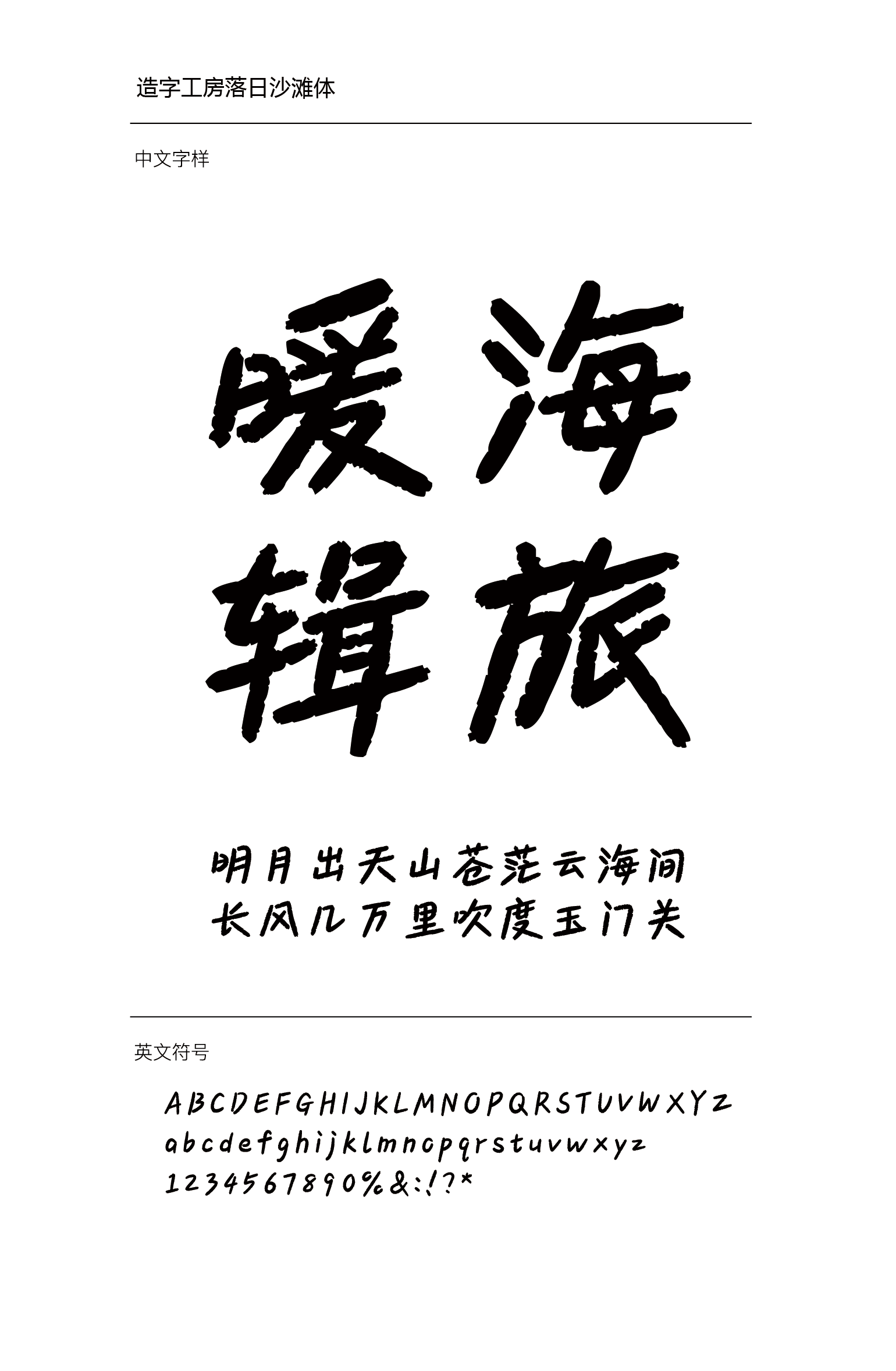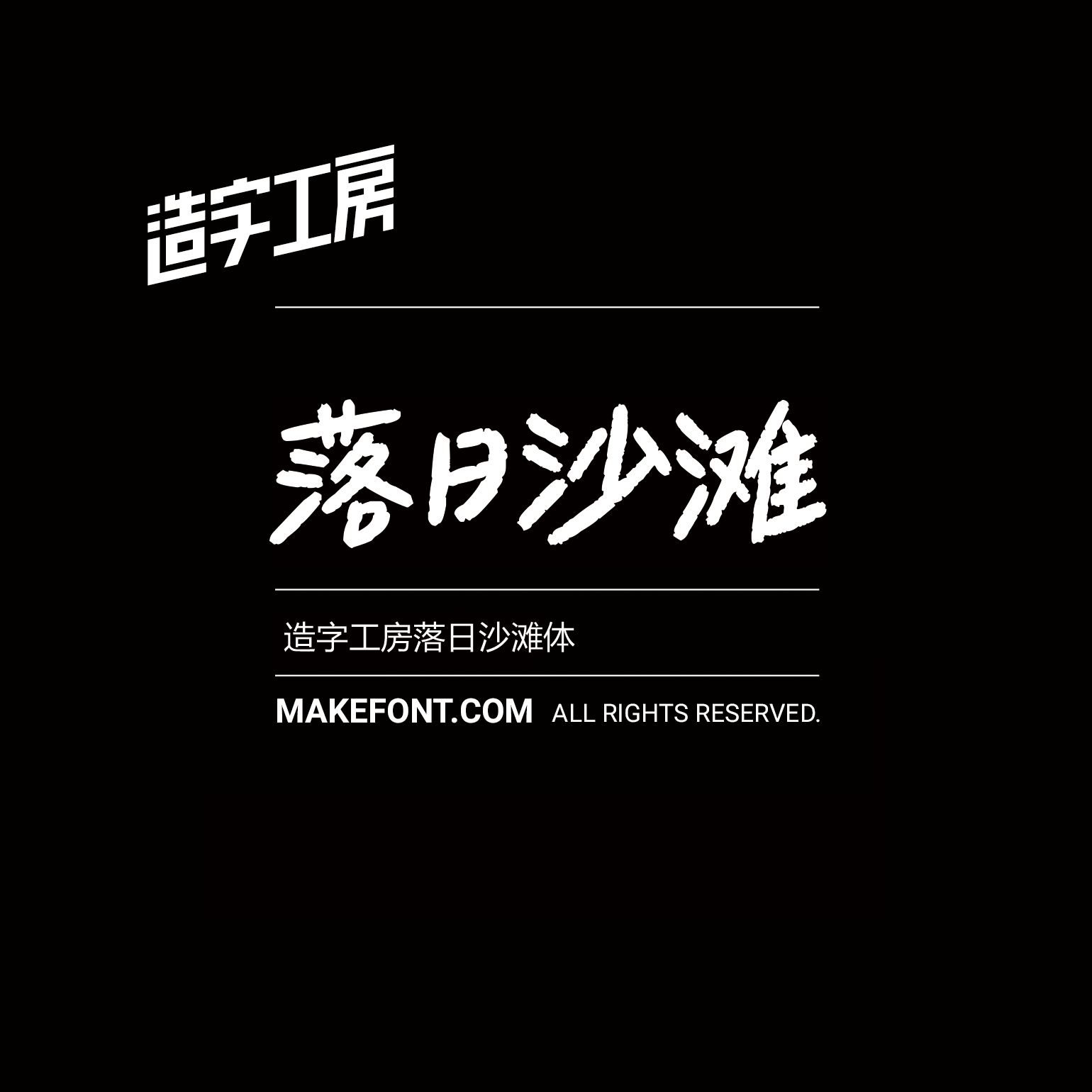
造字工房落日沙滩体设计说明
造字工房落日沙滩体,笔画轻盈随性,结构松散自在,风格清新治愈,运笔自然流畅,疏密得当,传递出字体的松弛与灵动,是一款适配日常笔记、海报等辨识度超高的字体。本字体为简体字库,采用OpenType/CID格式,Adobe-GB1-5编码。基于中华人民共和国GB2312-80字符集标准,另按需添加101个汉字。共收容字数6864CJK汉字,ASCII常用字符100个。